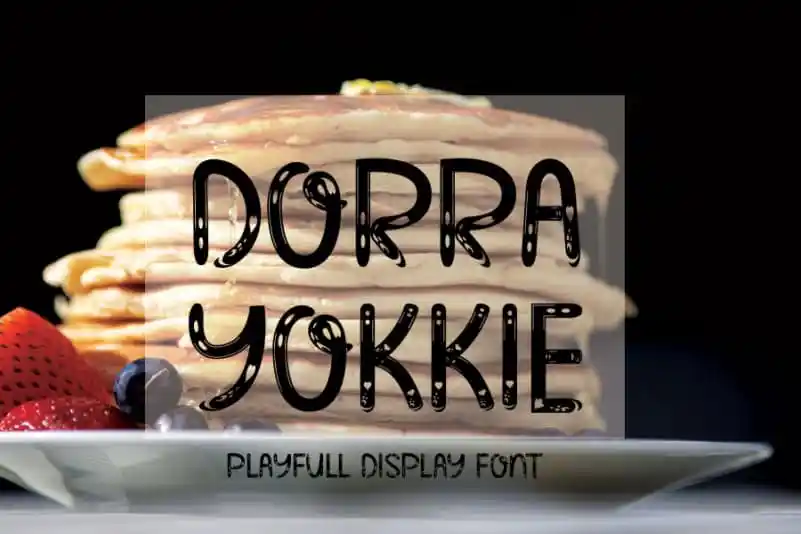
Dorra Yokkie Display Font – Download Grátis
A Fonte ‘Dorra Yokkie Display’ é uma delícia para os olhos, especialmente se você está procurando algo com cara de mão escrita mas que ainda traz a essência contemporânea e fresca de um tipo gráfico sofisticado. Essa fonte mantém seus influências chamativas da caligrafia ao mesmo tempo que é extremamente versátil. Suas capacidades permitirão que você use com facilidade em uma variedade de projetos, desde o formato final até o título e até os rascunhos para estaçãoaria. Sua sofisticação não impede que ela seja moderna e atual, o que a torna ideal para quem está buscando algo especial e criativo para seus materiais impressos. A ‘Dorra Yokkie Display’ é perfeita tanto para designers de gráficos profissionais quanto para aqueles que estão procurando por um recurso visual único para seus projetos pessoais.